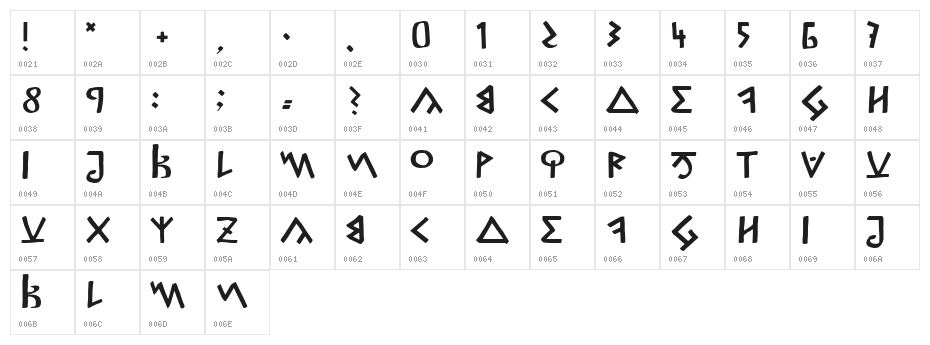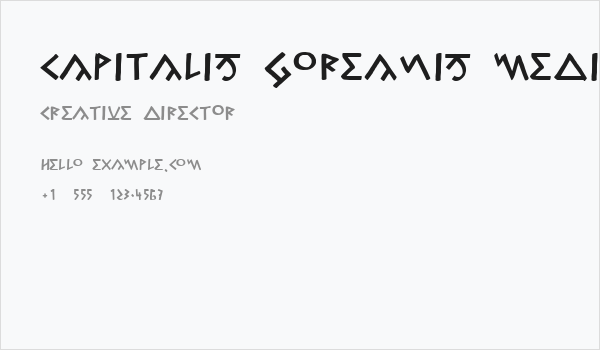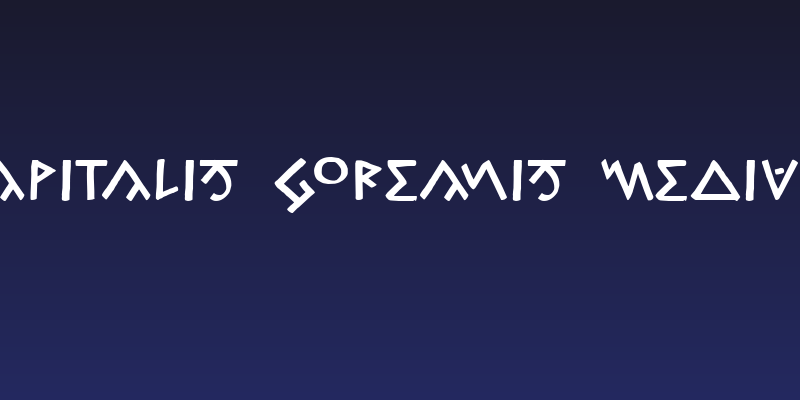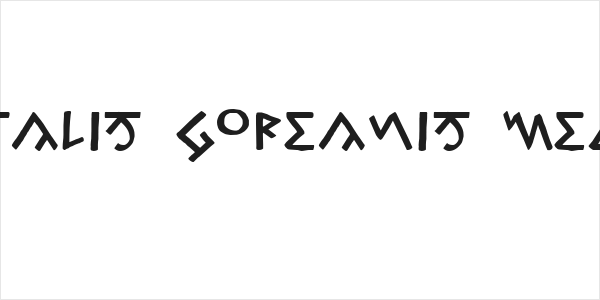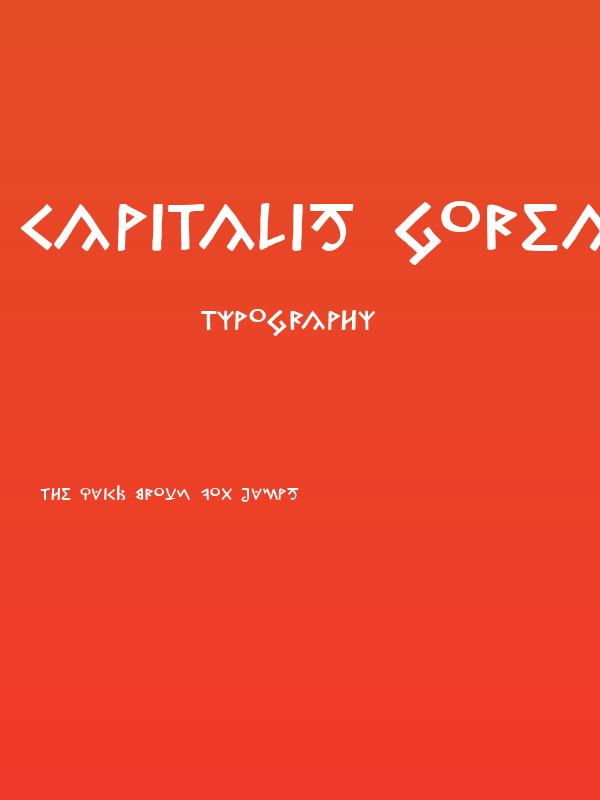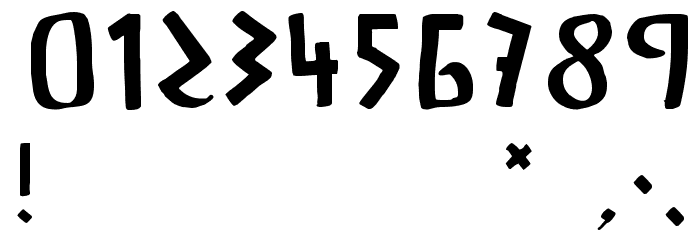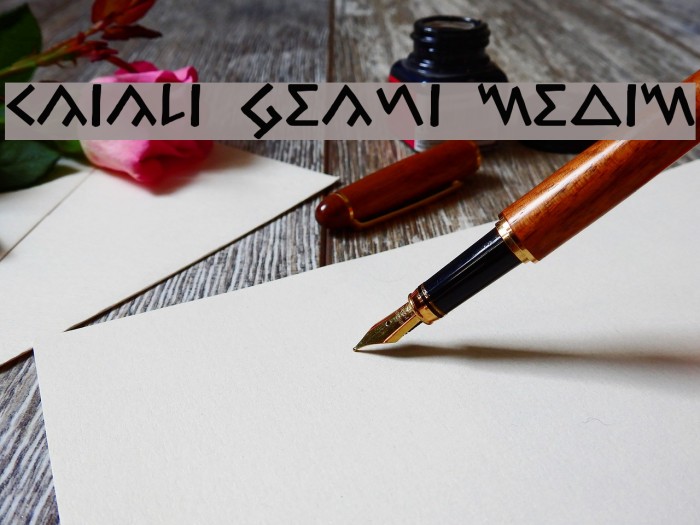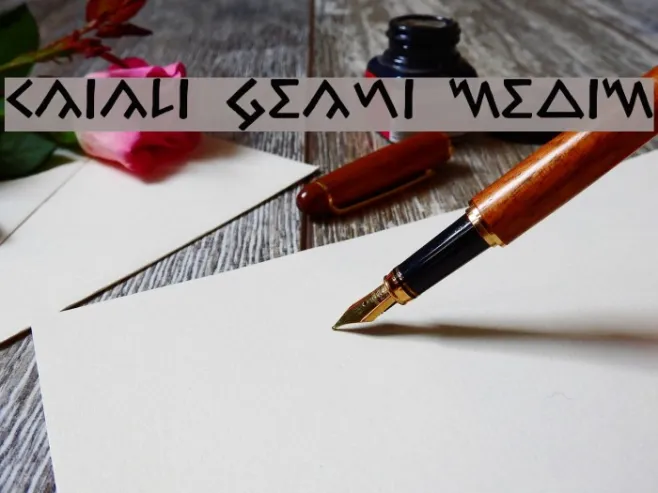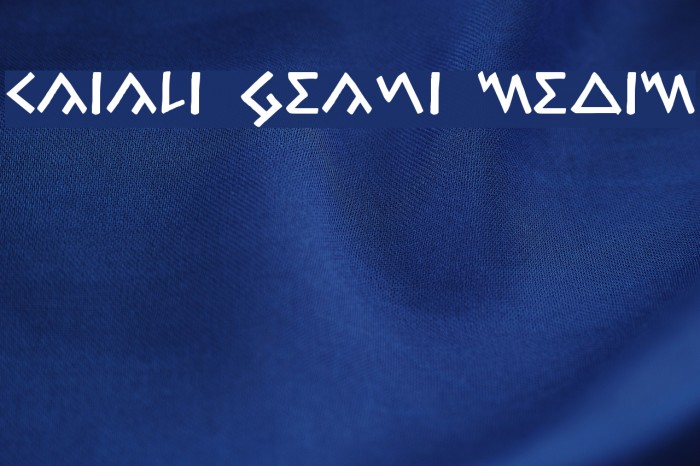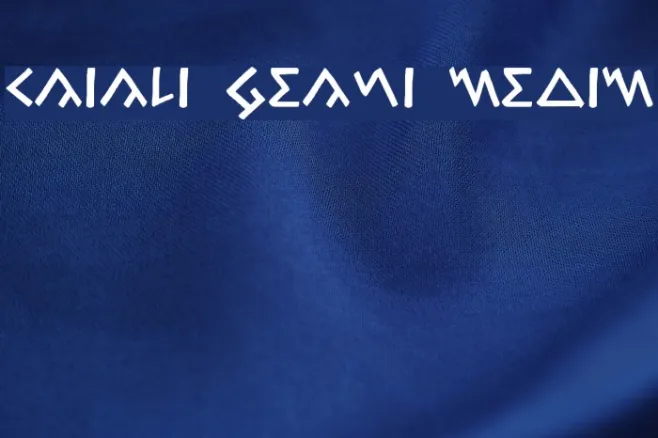
Capitalis Goreanis Medium Font
| Projets proposés | Ideal for fantasy-themed designs, historical posters, game titles, or any project seeking a mystical or ancient aesthetic. |